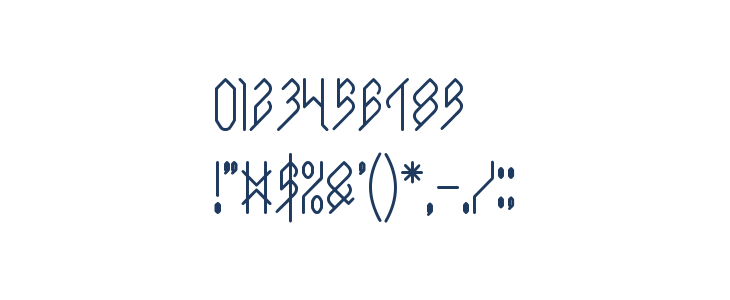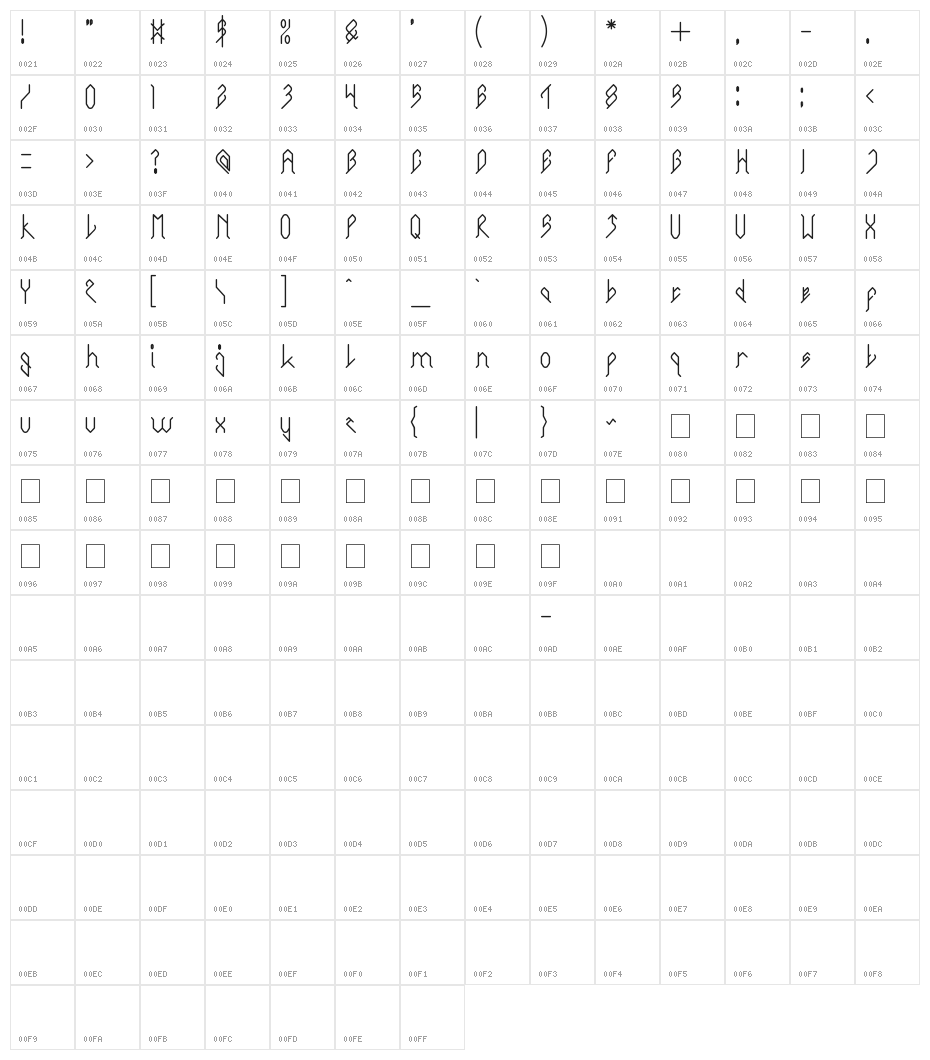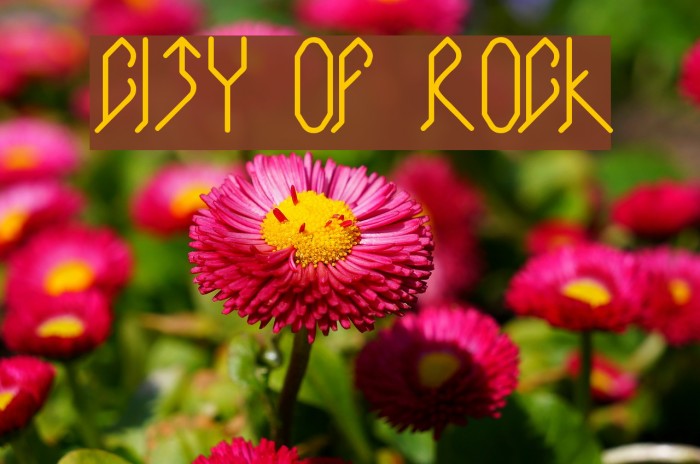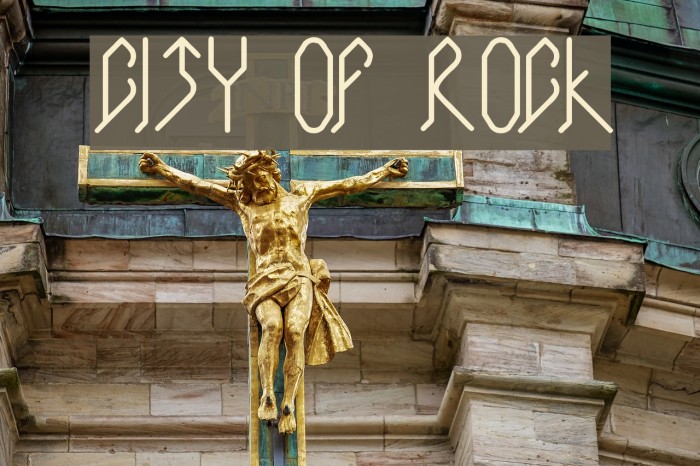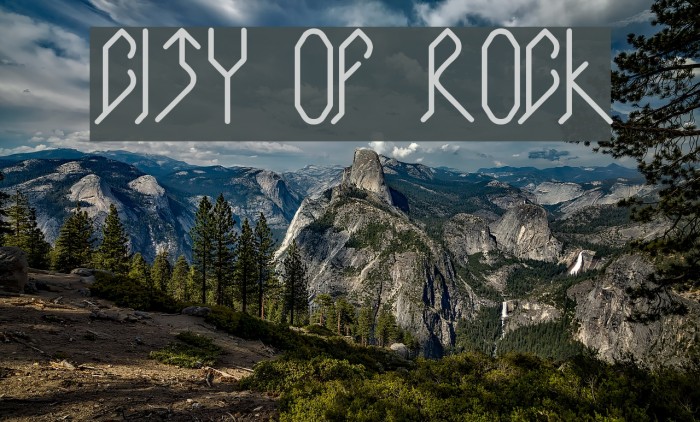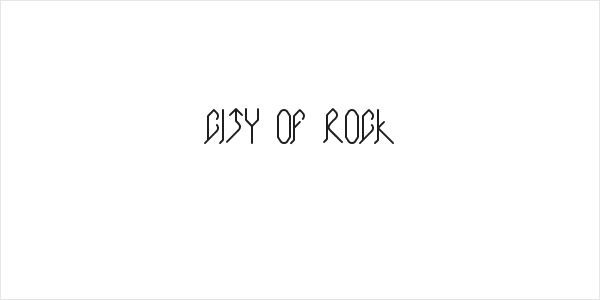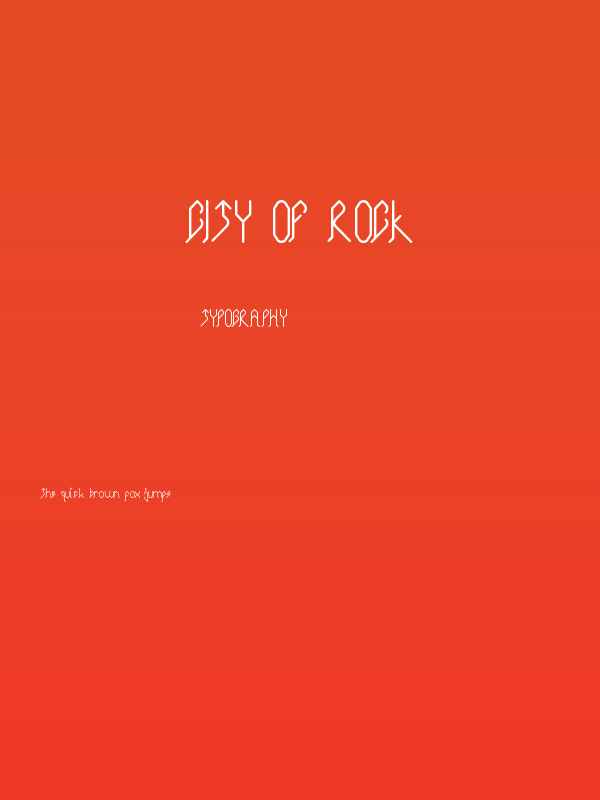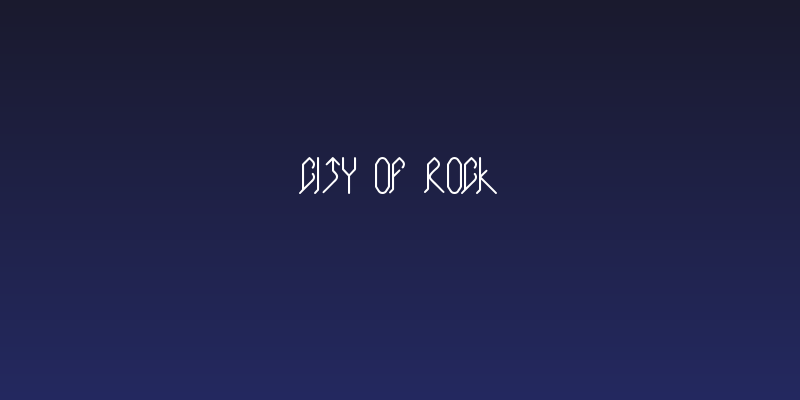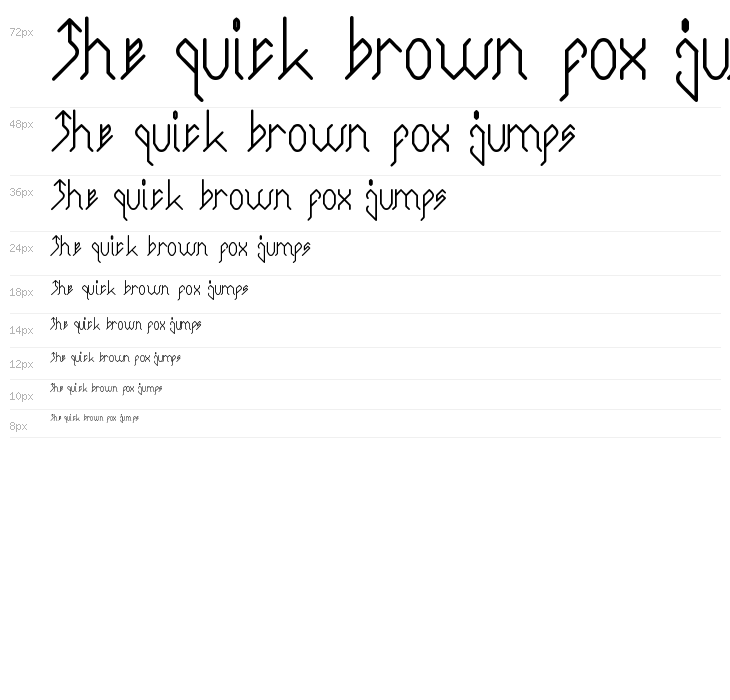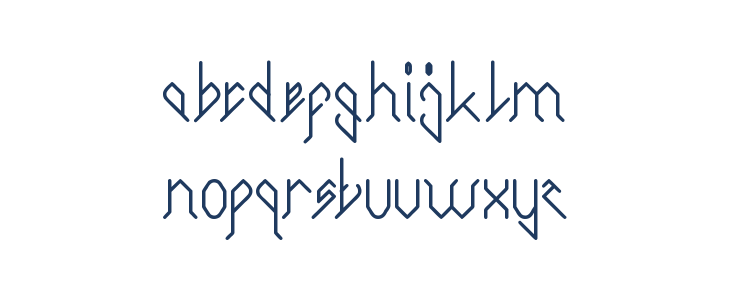
CITY OF ROCK Font
| Proyectos propuestos | Ideal for music album covers, video game titles, fantasy-themed posters, and branding for edgy or alternative products. |